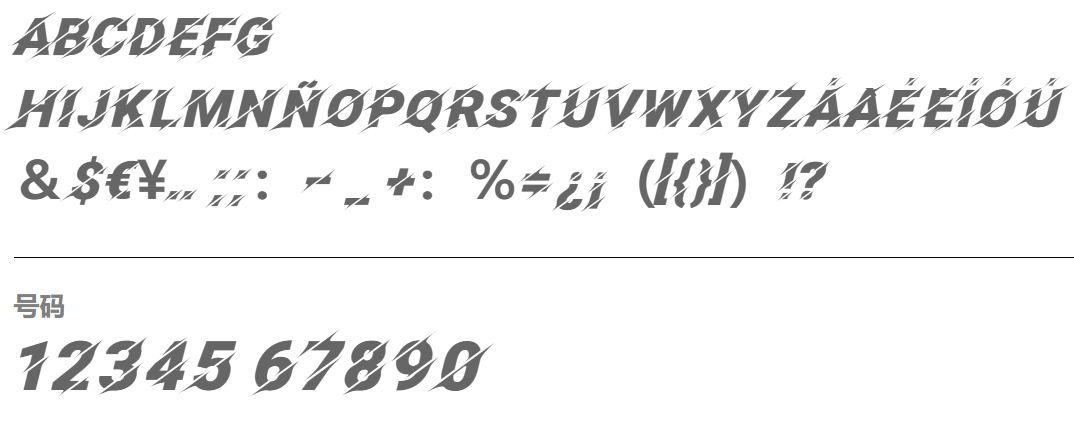
Facón是由Alejo Bergmann设计的运动外观字体。它功能强大,充满活力,并且完全独一无二。看起来就像忍者一样,将所有字母切成薄片,使字体具有醒目的效果。Facón是一种创意字体,可为任何设计增添“运动”感。它唤起了一种侵略性的美学,并且不断地运动,好像字体不能在一个地方停滞不前。
作者:阿莱霍·伯格曼(Alejo Bergmann)
Facón是由Alejo Bergmann设计的运动外观字体。它功能强大,充满活力,并且完全独一无二。看起来就像忍者一样,将所有字母切成薄片,使字体具有醒目的效果。Facón是一种创意字体,可为任何设计增添“运动”感。它唤起了一种侵略性的美学,并且不断地运动,好像字体不能在一个地方停滞不前。
作者:阿莱霍·伯格曼(Alejo Bergmann)